5月にメイリオの単独配布が始まっていたが(XP対象)、それに加えて中韓の新フォントもダウンロードできるようになっていたらしい。
配布されているのは簡体中文用の Microsoft YaHei(微软雅黑)、繁体中文の Microsoft JhengHei(微軟正黑體)、ハングルの Malgun Gothic(맑은 고딕)の3書体で、それぞれ Regular と Bold がある。メイリオと同じく ClearType での表示を前提にして作られた書体。
これは FontForge で開いてみたところ。上が YaHei、下が JhengHei。
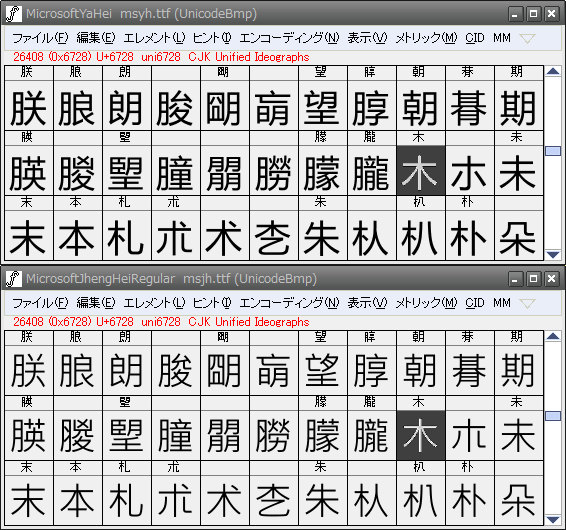
YaHei はメイリオと共通の表情を持っている。また同じ字を比較してみれば、JhengHei(台湾デザイン)よりも YaHei(中国デザイン)の方が日本のデザインに若干近い。というわけで、YaHei の方が馴染みやすいかもしれない。一応「YaHei が簡体、JhengHei が繁体」ということになっているが、どちらの書体も繁簡の両方をカバーしている。
こちらは Malgun。このフォントには、漢字は含まれていないようだ。
この記事にもスクリーンショットがある。YaHei を見てみると、漢文の訓点に使われる「天」も中国デザイン*1になっている。なんかおもしろい。
ちなみに、メイリオに含まれていた謎のグリフ GID+20681*2は、YaHei, JhengHei, Malgun には見当たらなかった。
*1:1画目よりも2画目の方が長い。